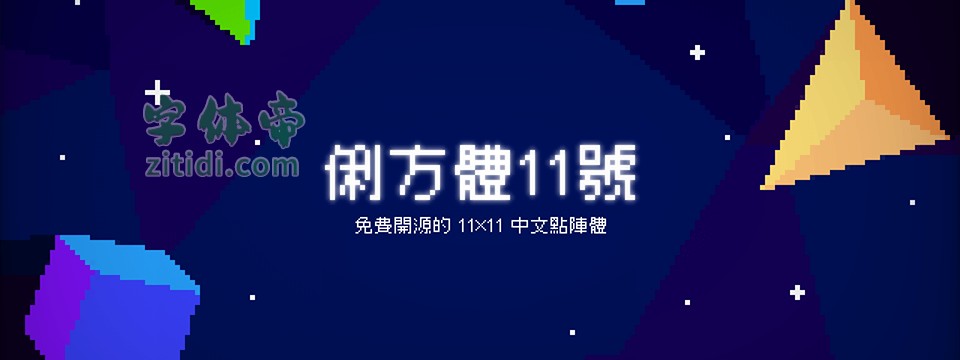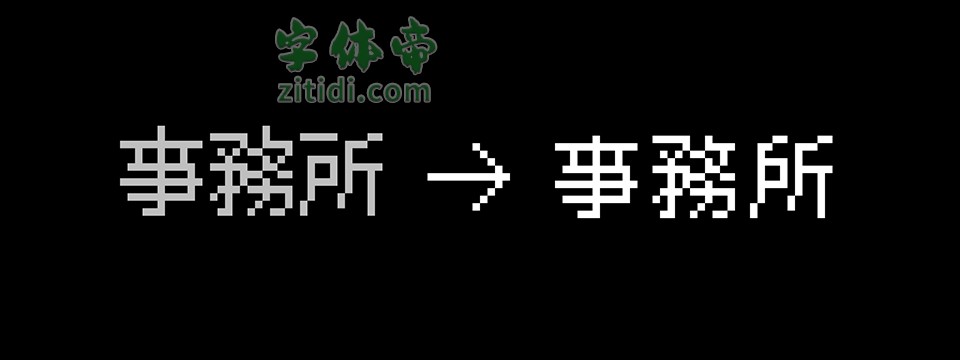
俐方体11号是基于M⁺ gothic 12r衍生的开源繁体中文点阵字型,可用于像素风格的游戏以及美术当中。
字形调整
本字型以日文字型 M⁺ gothic 12r 为基础替繁体中文进行修改与扩充,其中包括适用繁体中文的标点符号以及较符合台湾地区习惯的字形等。
收录字数
- 常用国字标准字体 4808 字。
- Big5 第一字面 5401 字。
- IICore 台湾常用字 T1A、T2A 及部分 T2B。
- 台客闽粤字。
- 注音符号。
- GB 2312 Level-1。
- 通用规范汉字表 一级。
- 元素週期表之所有元素字符。